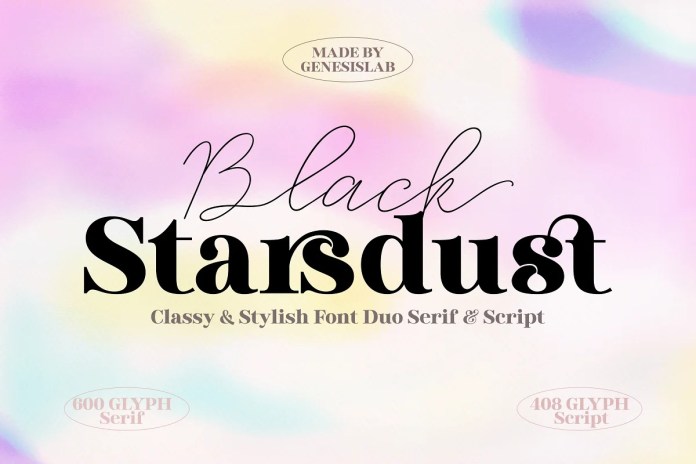
Black Starsdust 字体
它是由Genesis Lab创建的优雅而优雅的字体组合,具有现代感。Black Starsdut 是一种独特而现代的组合衬线字体,辅以混合替代品,赋予其奢华而独特的风格。这种字体非常适合品牌、徽标、邀请函、水印等。
Black Starsdut 字体采用双字体样式、细字体和粗体。全字体,包括大写和小写、连字、任意、数字、汤脚本、超级脚本标点符号、替代斜体和多语言支持。
设计师 :创世纪实验室